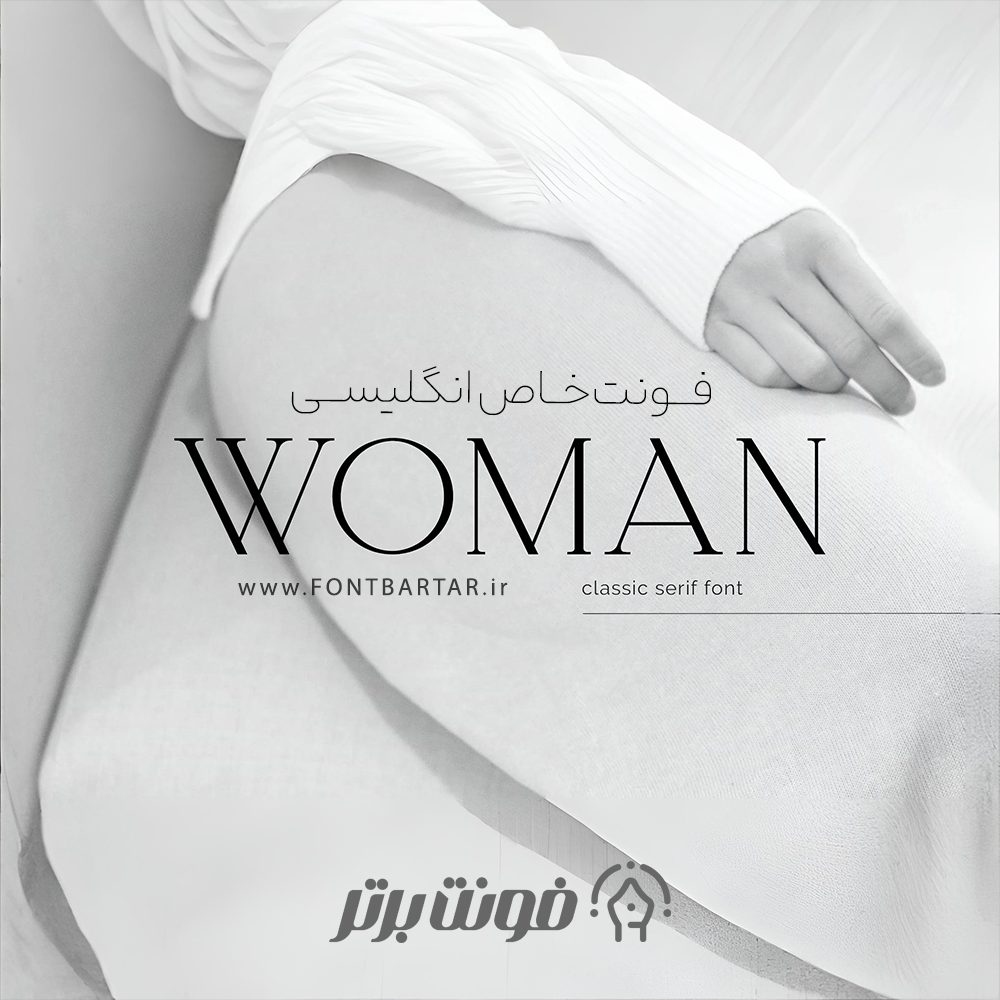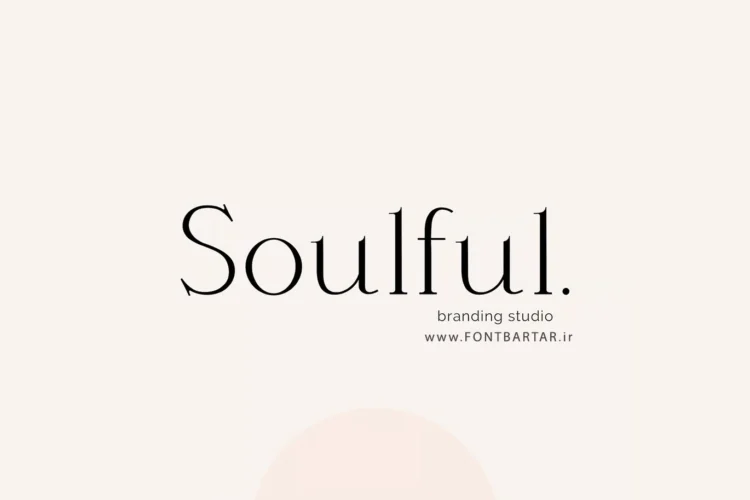
دانلود فونت خاص انگلیسی WOMAN – فونت کلاسیک و ظریف برای طراحیهای لوکس
اگر به دنبال یک فونت خاص انگلیسی خاص و شیک با حس زنانه و لطیف هستید، فونت خاص WOMAN یکی از بهترین انتخابهاست. خرید فونت خاص با طراحی کلاسیک، خطوط ظریف و استایل مینیمال خود، برای ساخت لوگوهای مد، مجلات، برندهای فشن، و طراحیهای هنری کاملاً ایدهآل است.
فونت انگلیسی WOMAN توسط تیم فونت برتر (FONTBARTAR.ir) طراحی و منتشر شده و در سبک Serif کلاسیک، با ترکیبی از اصالت و مدرنیته ساخته شده است. این فونت در نگاه اول حس لوکس، حرفهای و زیبا را به بیننده منتقل میکند.
ویژگی های فونت خاص WOMAN :
- حروف بزرگ/کوچک، اعداد، علائم نگارشی؛
- معمولی، ایتالیک، بولد.
💡ویژگیهای فونت انگلیسی WOMAN
- طراحی کلاسیک با ساختار Serif و ضخامت متعادل
- کاملاً مناسب برای طراحی لوگو، کاور مجله و برندهای زنانه
- دارای حروف کامل انگلیسی با جزئیات دقیق و خطوط نرم
- فونتی مدرن و خوانا برای طراحی مینیمال و حرفهای
کاربرد فونت WOMAN در طراحی
فونت WOMAN به دلیل ظرافت و اصالت طراحی خود، انتخابی ایدهآل برای طراحانی است که به دنبال فونت خاص و متمایز هستند.
این فونت بهویژه برای:
- طراحی لوگوی برندهای فشن و بیوتی
- ساخت کاور مجله و پوستر تبلیغاتی
- فونت خاص برای اسم
- طراحی کارت دعوت یا بستهبندی لوکس
- طراحی پستهای اینستاگرامی با استایل خاص
بهخوبی عمل میکند.
۱. فونت WOMAN برای چه نوع طراحی مناسب است؟
این فونت برای طراحیهای مرتبط با مد، زیبایی، برندهای لوکس و طراحیهای گرافیکی مینیمال بسیار مناسب است.
2. آیا فونت WOMAN از حروف کوچک و بزرگ انگلیسی پشتیبانی میکند؟
بله، این فونت شامل حروف کامل الفبای انگلیسی به همراه اعداد و نمادهای پایه است.